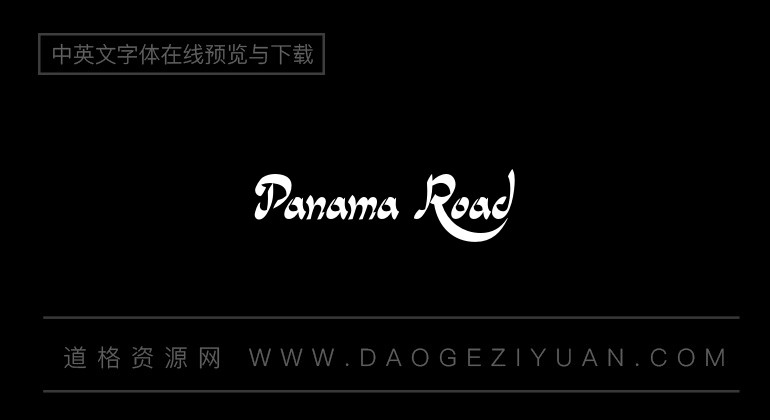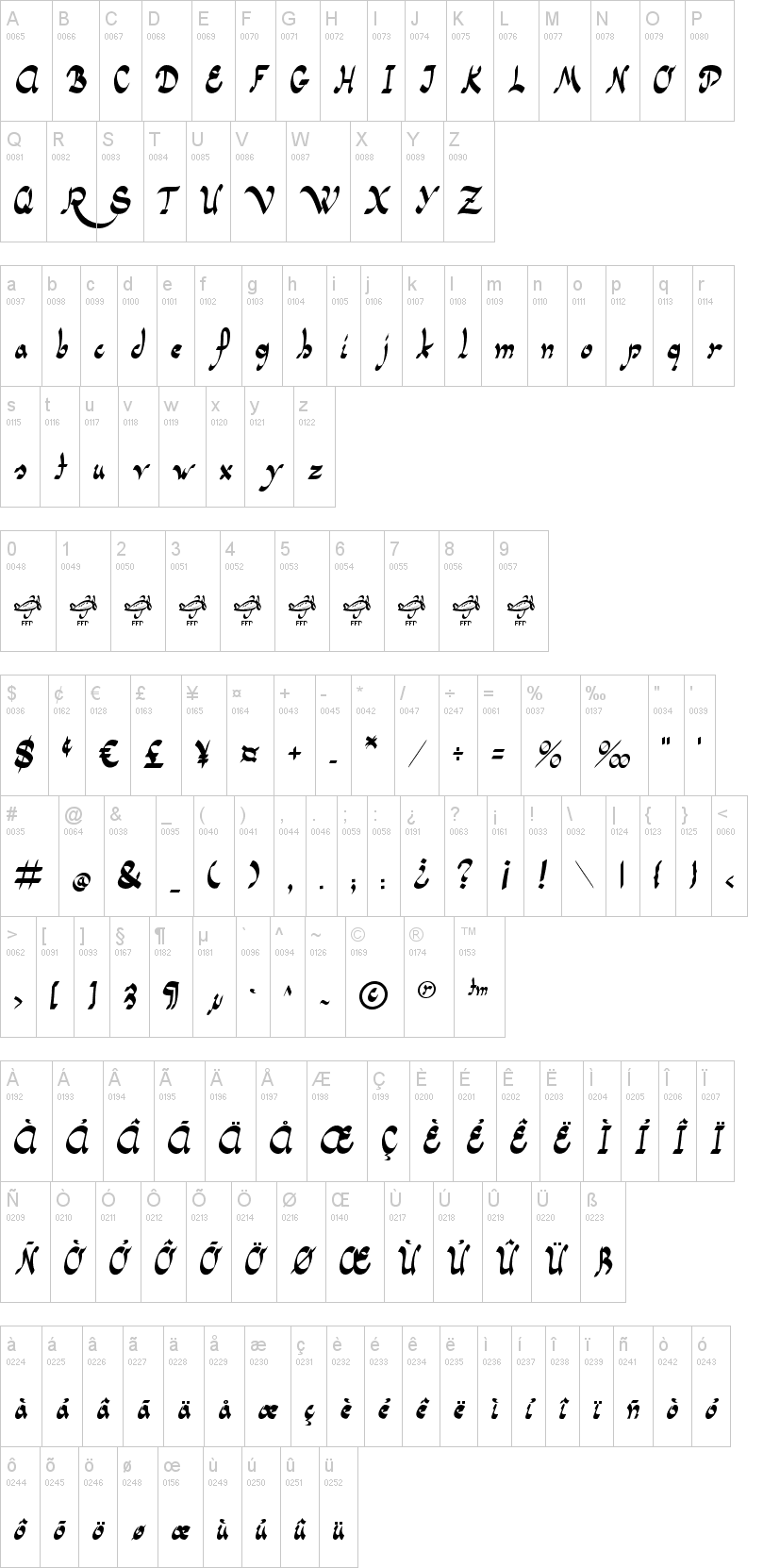
Panama Road 是一种手写风格的字体,灵感来自于中美洲和加勒比海地区的手写标志和广告。它具有粗犷的笔画和独特的装饰性字形,让它在设计项目中非常突出和引人注目。 Panama Road 字体包括大写字母、小写字母、数字和标点符号,适用于许多设计项目,如海报、标志、包装和书籍封面等。它的笔画具有不规则的形状和变化,使每个字母看起来都非常独特,适合需要突出个性和特点的设计。 此外,Panama Road 字体还包括了一些额外的装饰元素,如箭头、手势和图形,这些元素可以用于增强设计的视觉吸引力和表现力。总的来说,Panama Road 字体是一种非常适合用于富有创意和特色的设计项目的字体。内容介绍
Panama Road是一款非常不错的手写艺术字体,具有很好的视觉感,适合于文化类的宣传设计、商业类品牌的广告和产品包装设计以及个性化文字排版等较多场景。